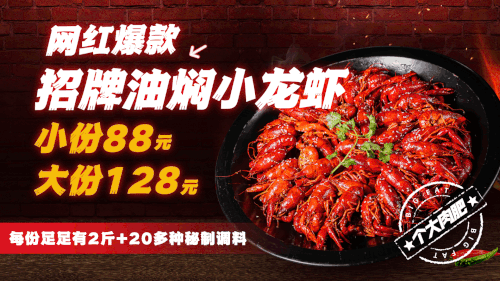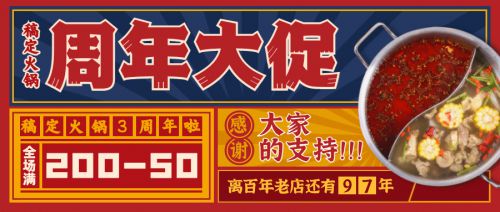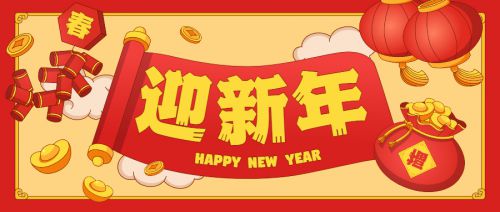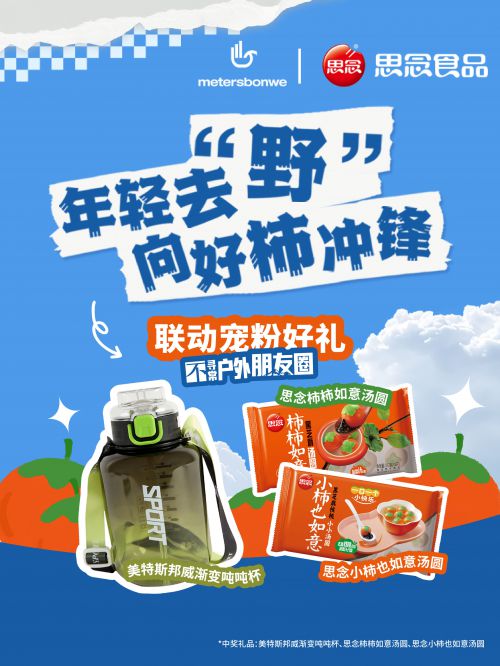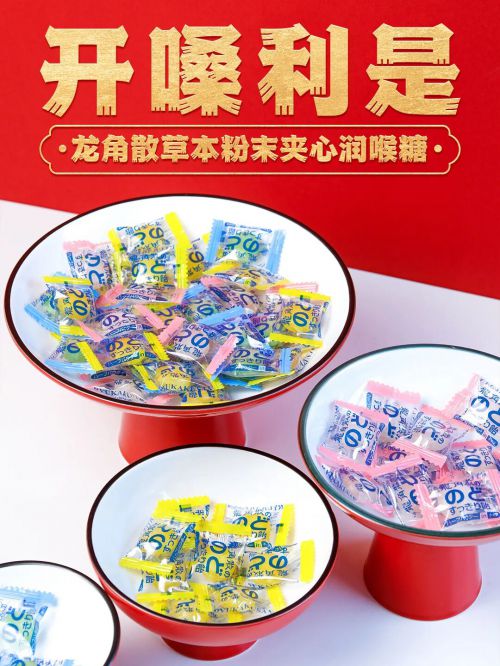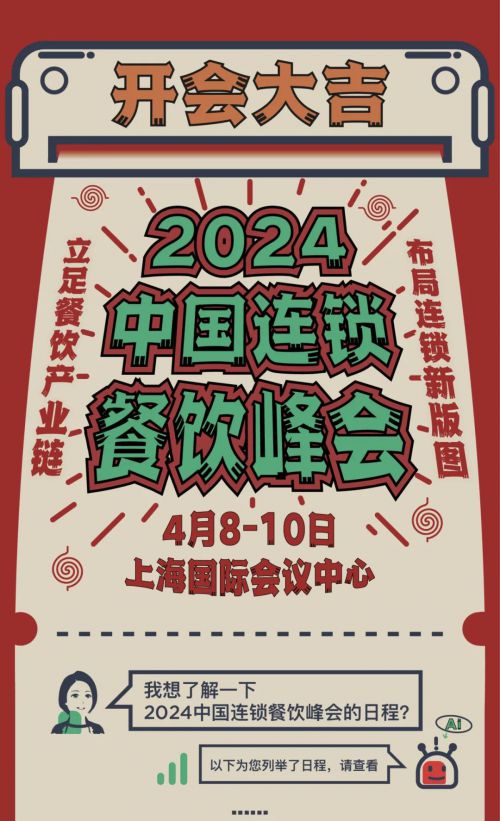
点字江户招牌黑
点字江户招牌黑灵感来源于日本江户时期的文字特征,笔画装饰融合日式书写特征,造型大胆夸张,字型厚重具有非常稳重的力量感。点字江户招牌黑字体整体字面方正,字体结构疏密合理在笔画极粗的情况下保证了字体本身的通透性,笔画起承顿挫飘逸流畅,朴拙中不失灵动。可被广泛应用在包装和电商等方面。
卢鑫亚
90后字体设计师,曾获第二届字体之星评委奖,最具商业潜力奖,第三届字体之星评委奖。